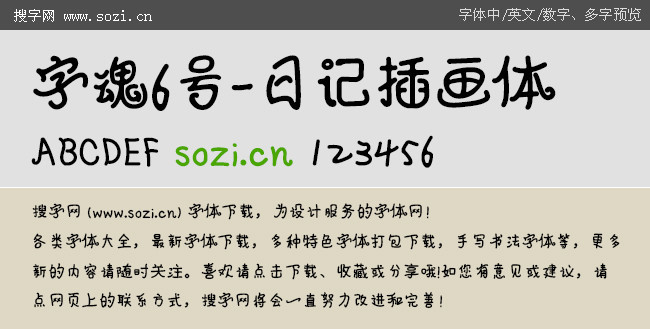
字魂6號-日記插畫體
搜字網(wǎng)提供一款字魂6號-日記插畫體中文字體下載,該字體是一款硬筆手寫卡通可愛字體,該字體包含6763個中文、字母、 符號和數(shù)字,具有可愛、卡通、趣味 的風格,可以滿足您設計上的各種需求,該字體主要用于店鋪、美食餐飲、青春校園、影視傳媒、新媒體、電商 等場景。